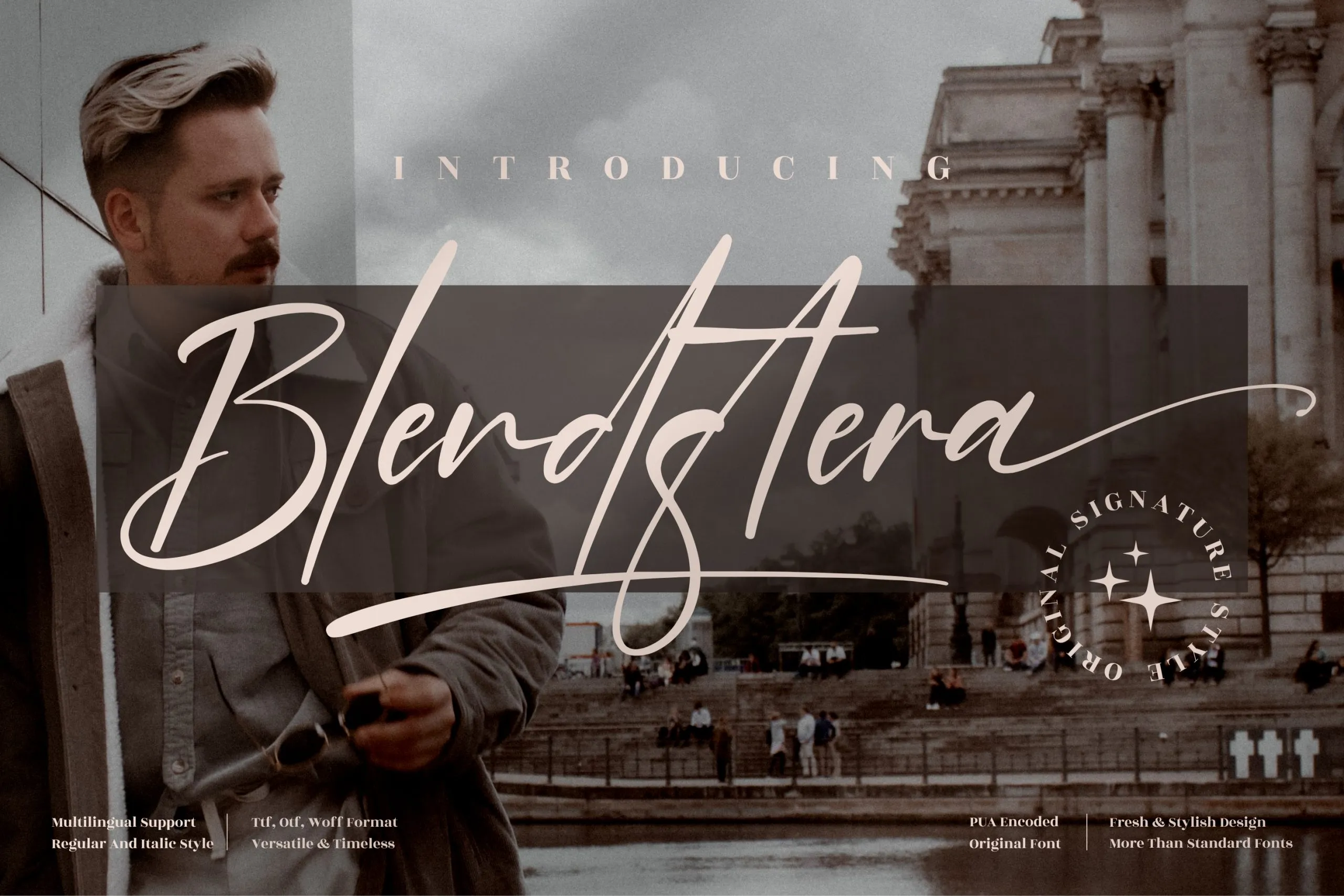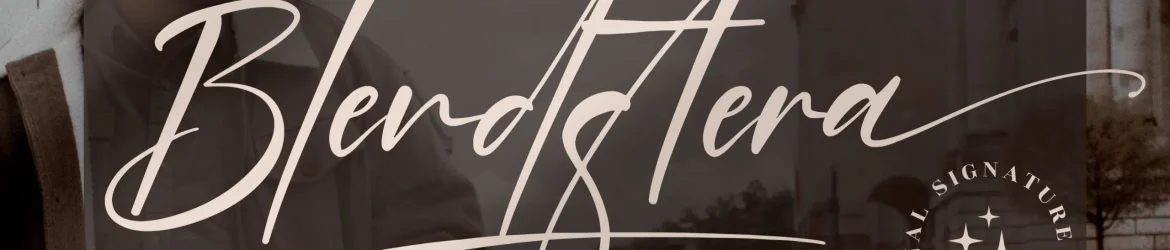
Blendstera Font é uma elegante assinatura-font que pertence à coleção exclusiva do designer perspectype. Este moderno tipo de letra é perfeito para qualquer projeto criativo, seja ele de marca, design de mobília, embalagens de produtos ou até mesmo na ilustração de capas de livros e cartões de nome. Seja qual for o seu trabalho de arte, Blendstera vai trazer um toque único e sofisticado a seus projetos, garantindo uma aparência premium que certamente capturará a atenção dos seus clientes. O Blendstera Font é um ótimo complemento para qualquer design que busque ser notável e personalizado, seja em estampas de mugs, panfletos, cartazes ou até mesmo em assinaturas de eventos especiais. Uma escolha certeira para aqueles que desejam dar um toque único a seus projetos sem abrir mão da qualidade premium do design.